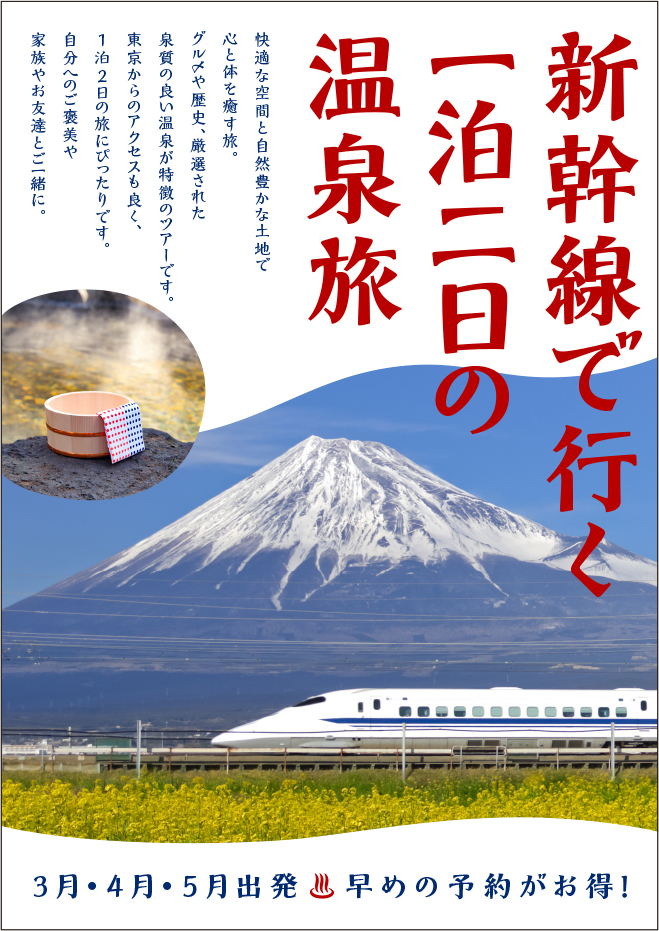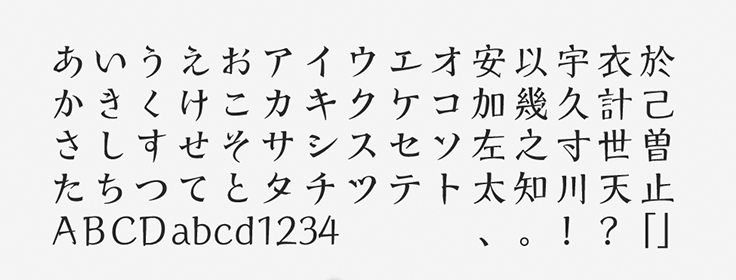
「モアリア」について
モアリアは2007年から提供され続けているデザインフォントです。明朝体にかなり近い要素を持ちながらも、伸び伸びと動き回る自由なエレメントで構成されています。かっちりとしすぎずに筆で書いたような勢いが表現されており、手書きテイストの表現にも役立つフォントです。
「モアリア」の特徴
縦画と横画の太さは明朝体に似ているため、馴染みのある親しみやすい印象を与えます。まるで強さと柔らかさをあわせ持ったようなオリジナルのスタイルで、本文はもちろんタイトルやコピーなどのさまざまな箇所で活躍するフォントです。
横画やハライの先などは押さえを控え、軽いタッチに仕上げられています。そのことが、散って消えていくような優しいイメージにもつながります。和テイストや日本の文化を表現したいシーンにもマッチし、どこか昭和レトロな雰囲気も漂うデザインです。
特徴的なエレメントでデザインされた温かみのあるフォントです。明朝体ではない「ちょっと面白いフォントを使いたいな!」というときのために覚えておくと良いでしょう。インパクトを狙いたいときに、ぜひ使いたいフォントです。